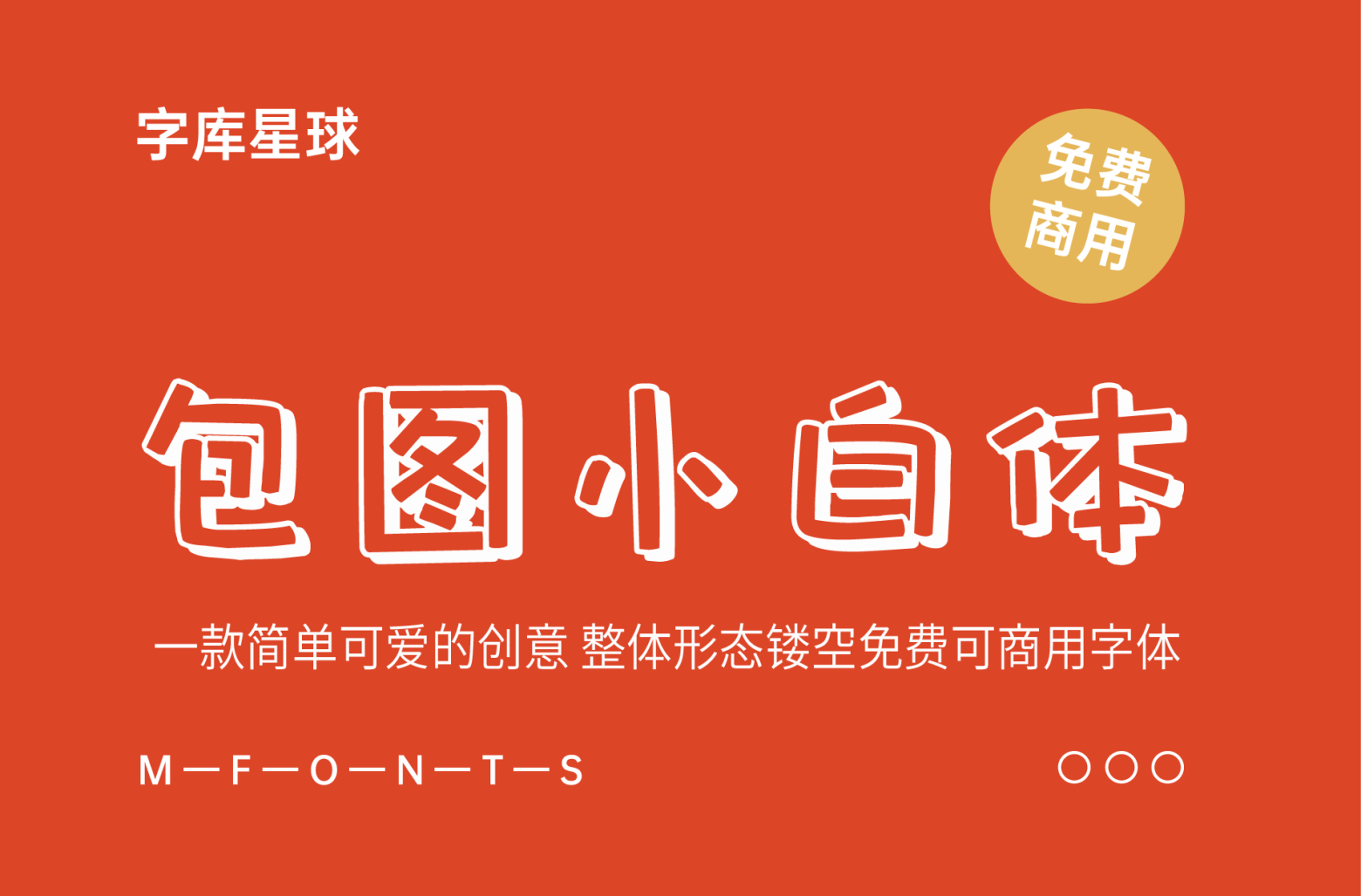
包图小白体, 定义为一款简单可爱的创意字体。在字形笔画上去除了折笔的弧形,换之以平直的笔画,竖弯钩转为竖折,同时弱化了钩笔画,省去了许多笔画末尾的小尾巴,显得更加直白可爱。粗短的笔画,像柯基的小短腿,相比细长的字体能给人更多的轻松感。整体形态采用了镂空的制作技巧,增强了字体的立体感,适合用于品牌标志、海报、包装、影视综艺、游戏、漫画等场景。